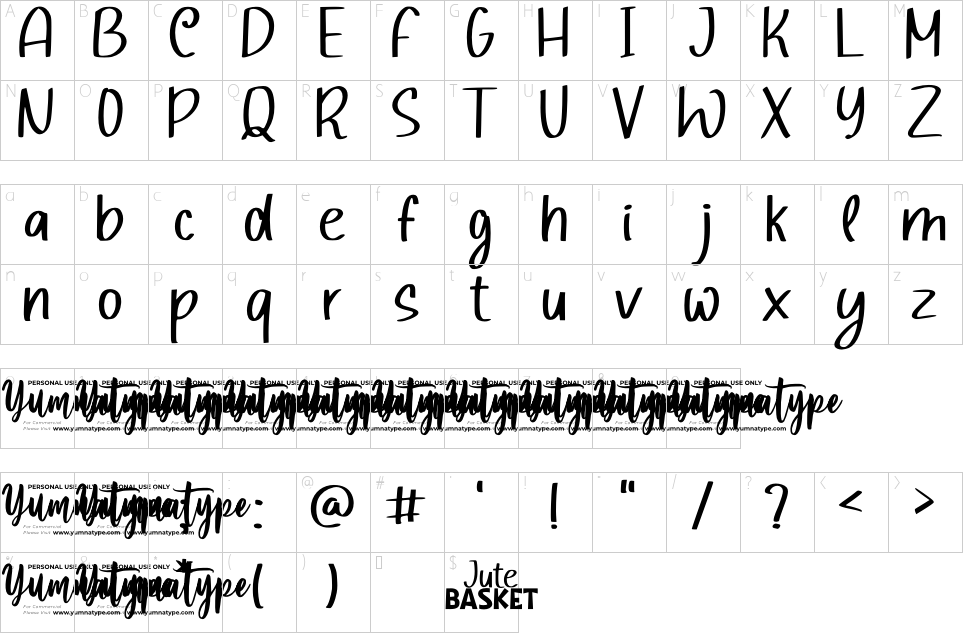
A fonte Jute Basket é uma escolha perfeita para qualquer designer gráfico que busca um estilo moderno e moderno. Desenhada pela Yumna Type, Jute Basket oferece linhas arredondadas e tipografia curvilínea que transmitem uma sensação de conforto e acolhimento. Esta fonte é perfeita para uso em design de identidade de marca, logotipos, e até mesmo para criar uma atmosfera amigável em sites ou aplicativos. Com sua simplicidade e beleza, Jute Basket é uma opção versátil que ajuda a destacar seu design. A fonte já foi baixada 4,002 vezes, demonstrando sua popularidade e qualidade. Jute Basket é uma fonte gráfica gratuita que vale a pena explorar.